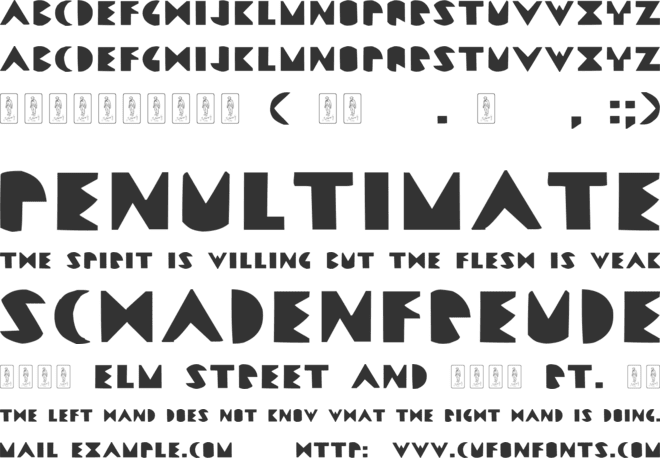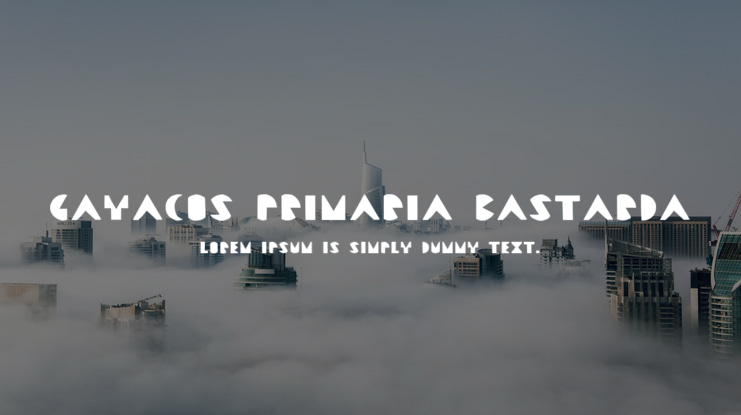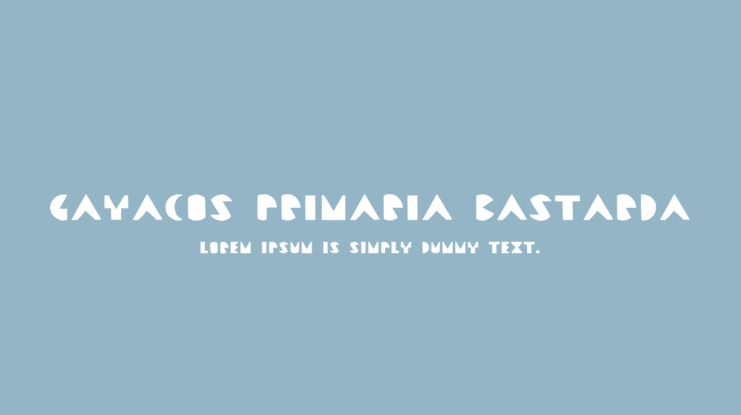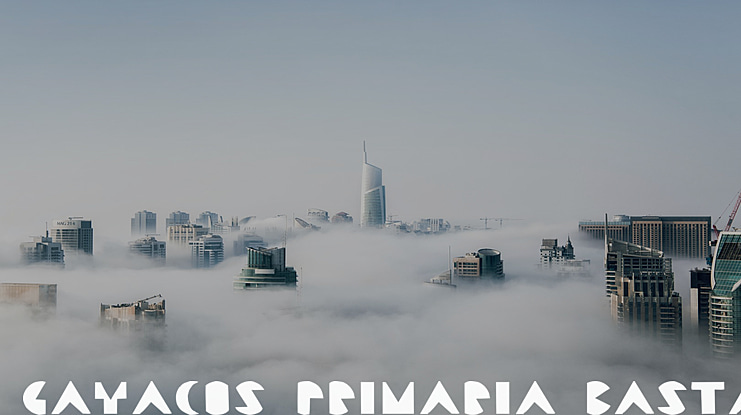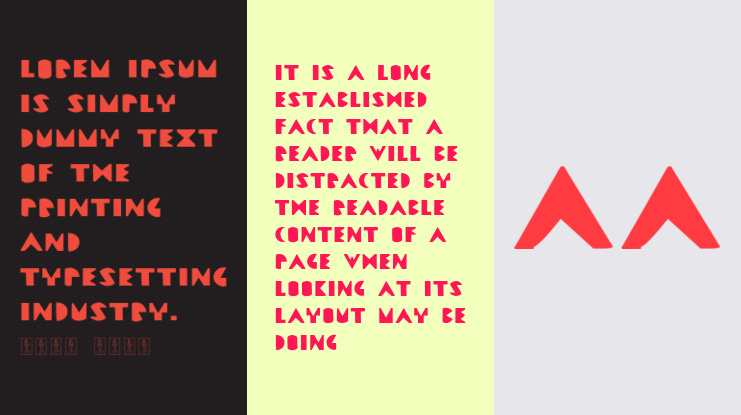
Gayacos Primaria Bastarda Font
El fallido resultado de un ejercicio universitario.
"Gayacos Primaria Bastarda" fue el resultado de uno de los primeros ejercicios en la materia Tipografía 1 cátedra Cosgaya.